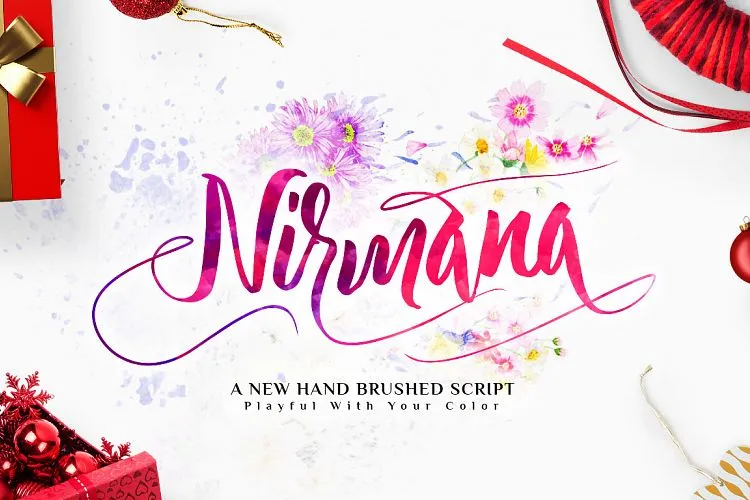
Descubra Nirmana Calligraphy Font, uma fonte de estilo calligrafia criada para atender às necessidades de projetos design futuros. Lançado pela designer Dirtyline Studio e disponível na CreativeMarket, esta premium font é agora gratuita para download. Nirmana Calligraphy Typefaces é um tipo de calligrafia feito à mão, ideal para diversas aplicações como títulos, assinaturas, logomarcas, cartas pessoais, convites de casamento, cabeçalhos de correspondência, sinalização, etiquetas, newsletters, posters e outros materiais. Sujeira ainda brilha, pois é versátil e pode ser usada para tudo isso. É a escolha perfeita para qualquer projeto que exija um touch elegante e único. Descubra o Nirmana Calligraphy Font e adicione sofisticação e personalidade ao seu próximo design!